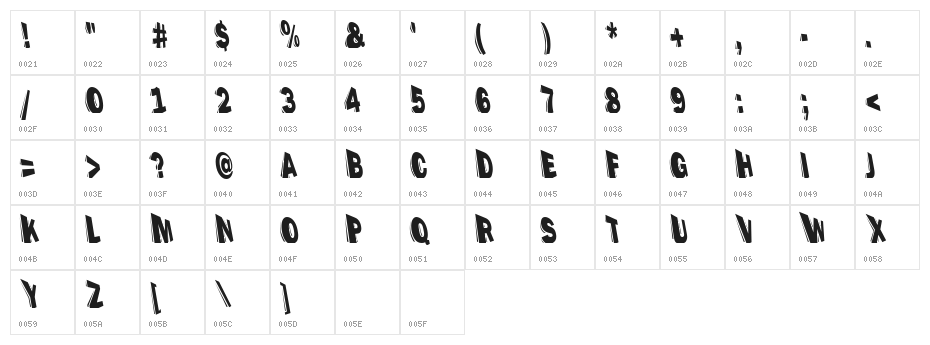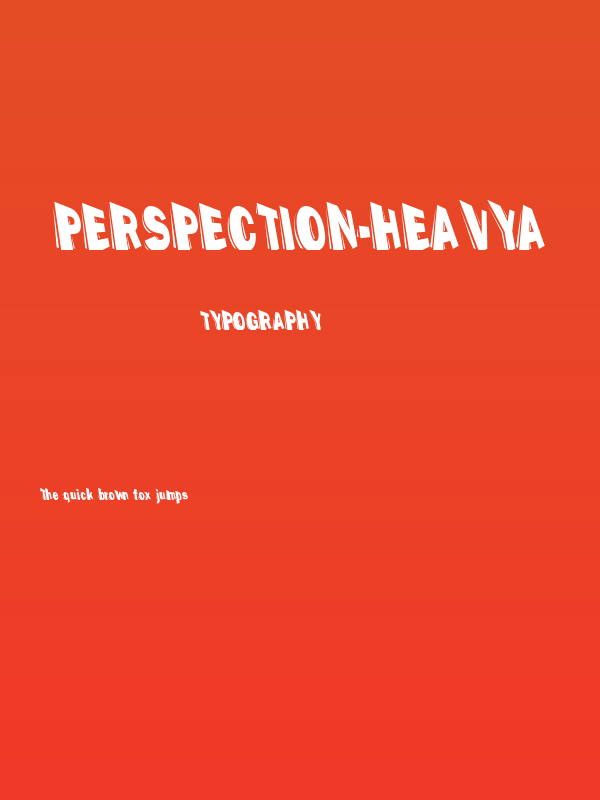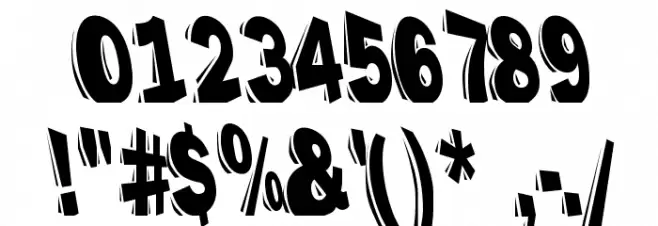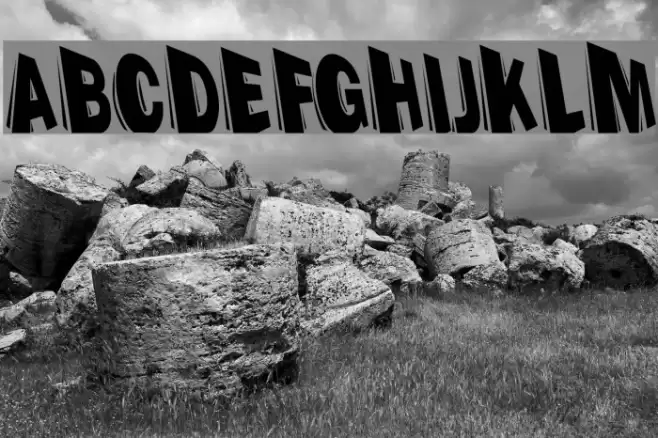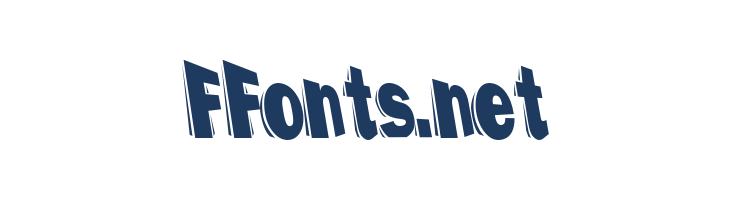
Perspection-HeavyA Font
✎ 3D
| Vorgeschlagene Projekte | Ideal for posters, advertisements, video game graphics, and branding materials that require a bold statement. |